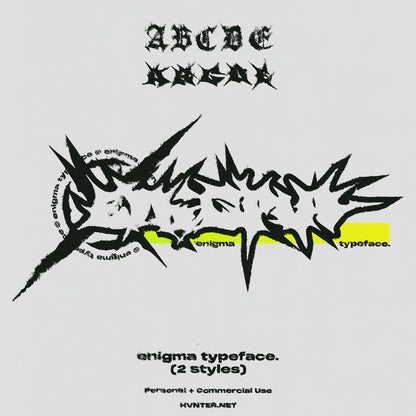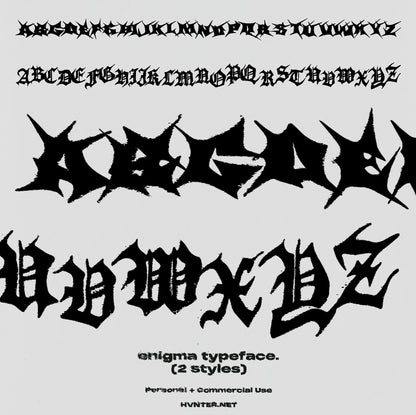
Enigma Typeface
Découvrez Enigma Typeface, une police de caractères audacieuse et distinctive qui apportera une touche unique à tous vos projets.
2 styles inclus (comme illustré dans les images)
Enigma Typeface est parfaite pour les designs qui exigent une esthétique forte et mémorable. Que ce soit pour des titres percutants, des logos expressifs ou des créations graphiques innovantes, cette police vous permettra de vous démarquer.